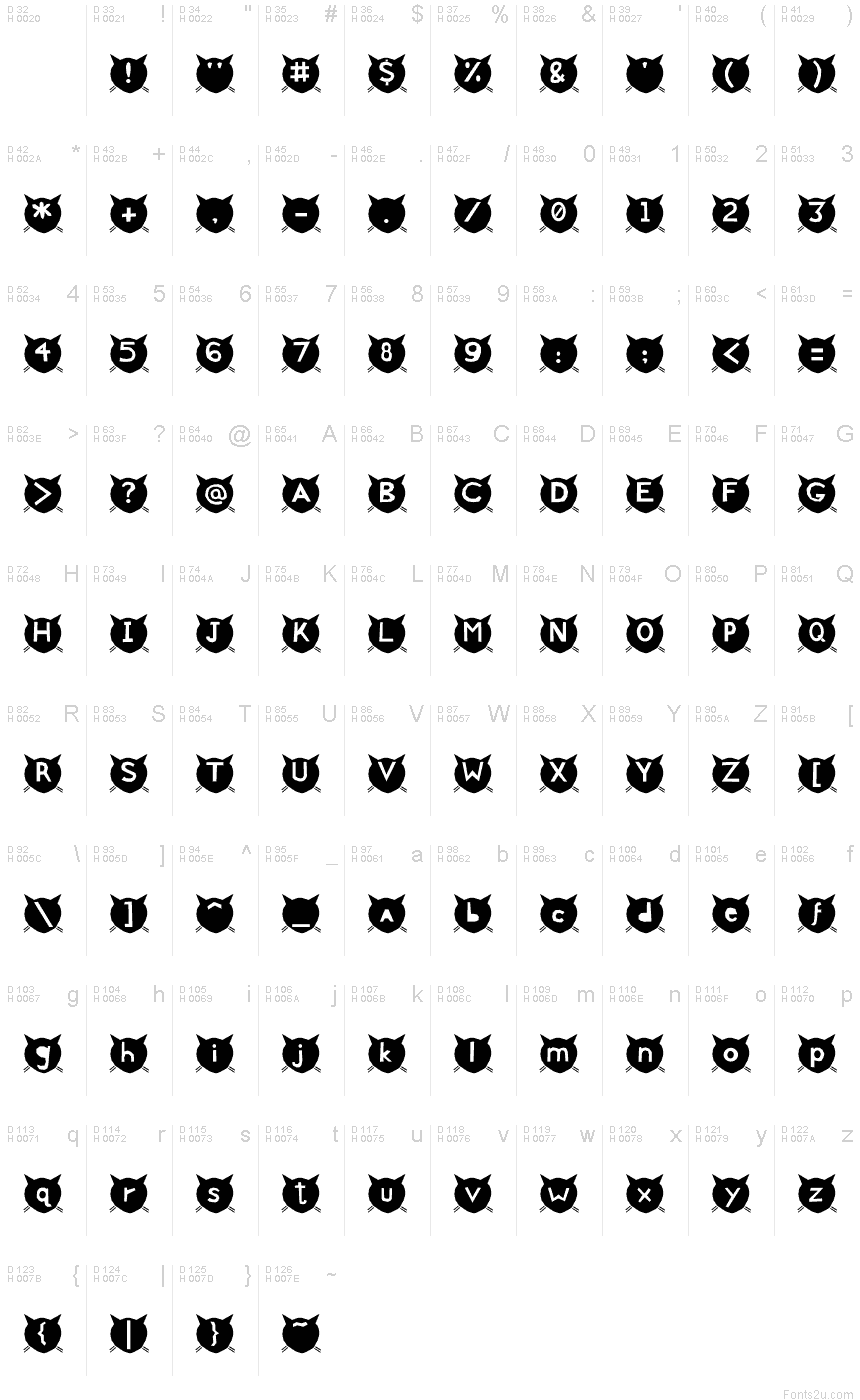
Il font Cats MEOW trasforma ogni lettera in una audace testa di gatto nera, con il carattere ritagliato in bianco per un effetto giocoso simile alla carta ritagliata. Le forme sono corpose e decise, con curve irregolari e sbarazzine che mantengono l'atmosfera leggera e informale, perfetta per qualsiasi progetto che richieda un tema felino divertente. Questo font gratuito dà il meglio di sé nelle dimensioni più grandi, dove le sagome dei gatti sono chiaramente leggibili e diventano parte integrante dell'impaginazione.
Utilizza Cats MEOW per copertine di libri per bambini, branding di negozi di animali, inviti a feste, adesivi, grafiche per i social media e poster a tema in cui desideri un richiamo visivo immediato. Le icone integrate lo rendono un mix tra tipografia e illustrazione, risparmiando tempo di progettazione e mantenendo la coerenza. Questo font gratuito si abbina bene a un semplice sans serif nei testi piccoli, così da lasciare che le forme dei gatti rimangano al centro della scena.